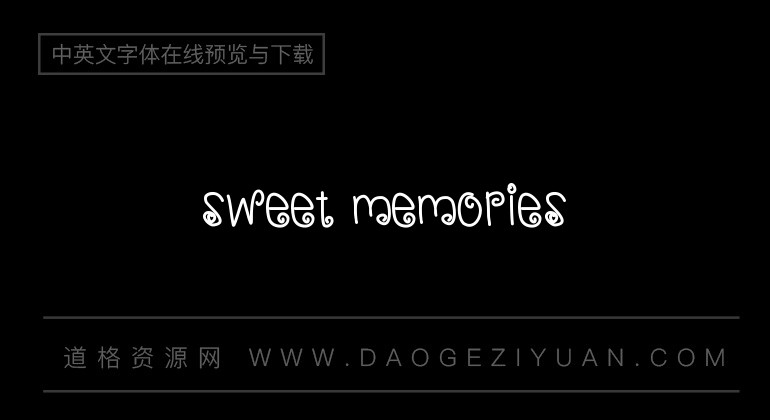
Sweet Memories
Sweet Memories 是一款充满甜蜜感的手写风格字体。它的设计灵感源自于手写日记和信件,让人联想到温馨、浪漫的回忆。这个字体具有良好的可读性和流畅的笔画,字母之间的间距也非常适宜,使得文字整体效果非常舒适、优美。Sweet Memories 字体适用于各种场合,特别是需要表现情感和感性的场合,如婚礼、纪念日和情人节等。使用它能够营造出一种充满温暖和浪漫的氛围,让人感到更加舒适和愉悦。
Sweet Memories是一款非常不错的手写艺术字体,具有很好的视觉感,适合于文化类的宣传设计、商业类品牌的广告和产品包装设计以及个性化文字排版等较多场景。